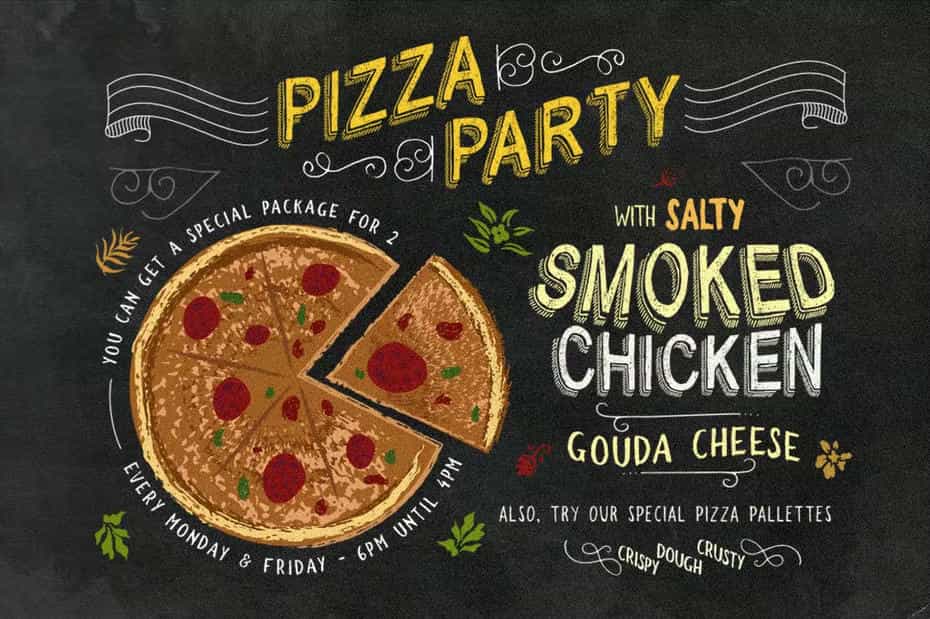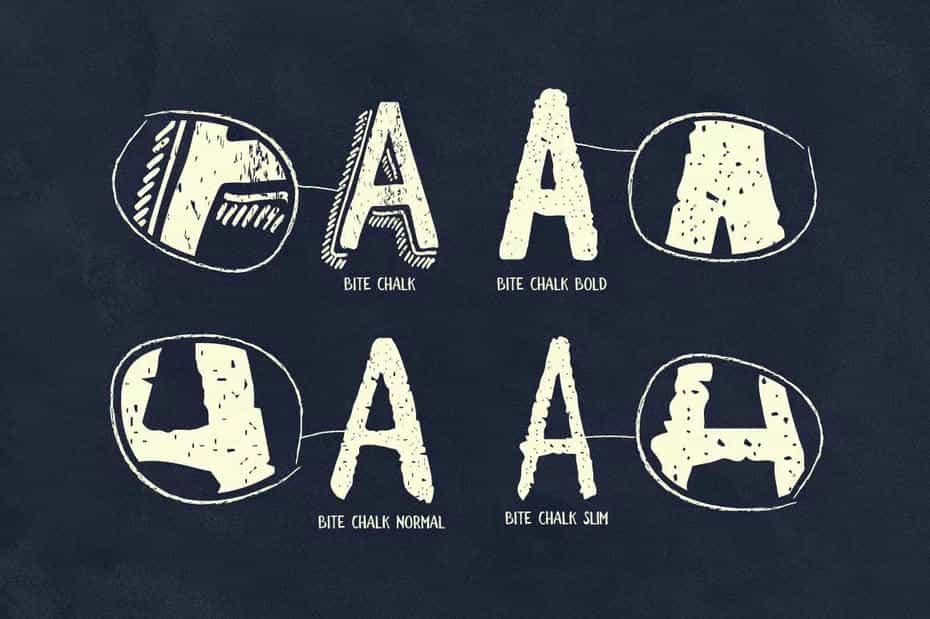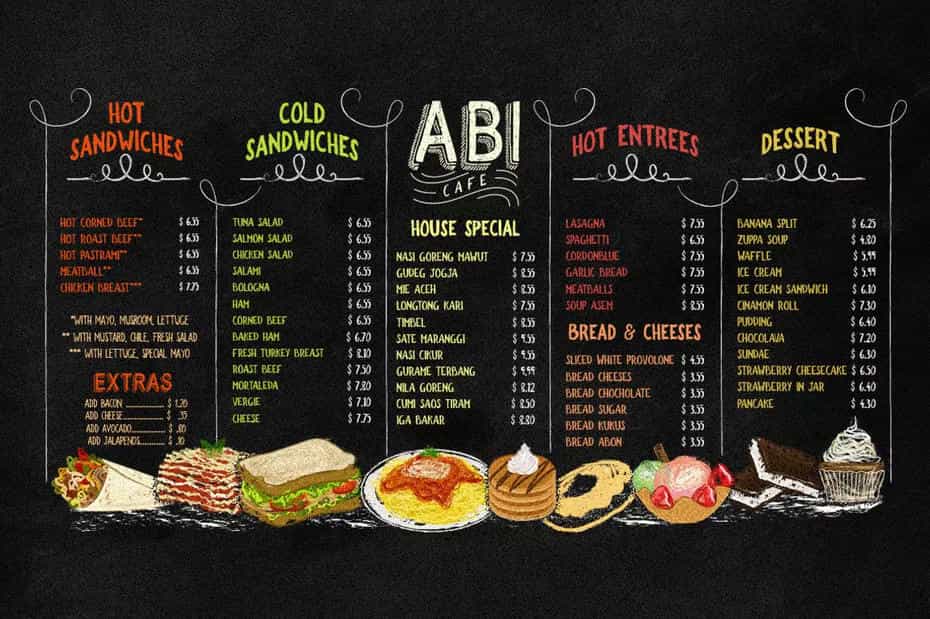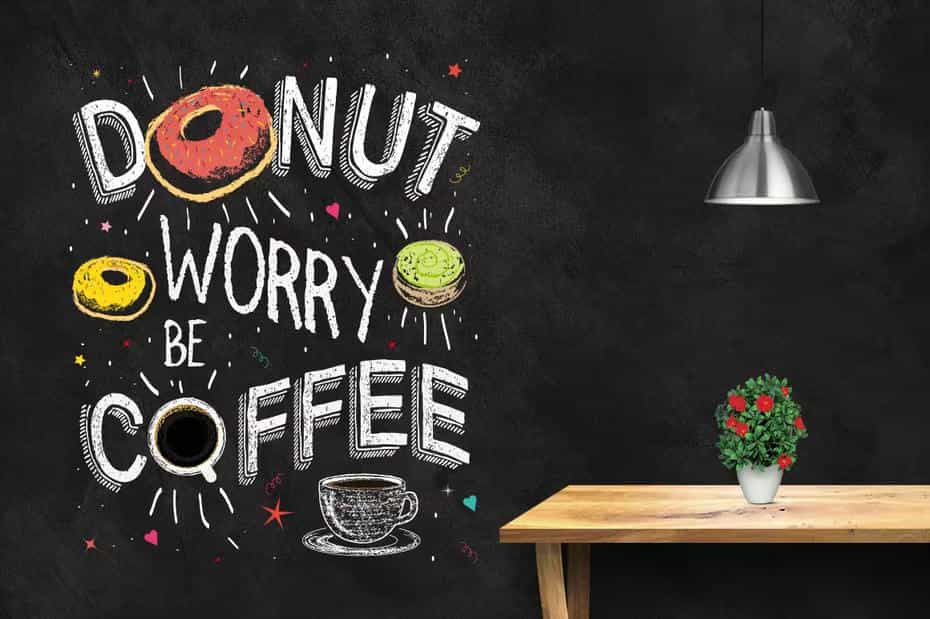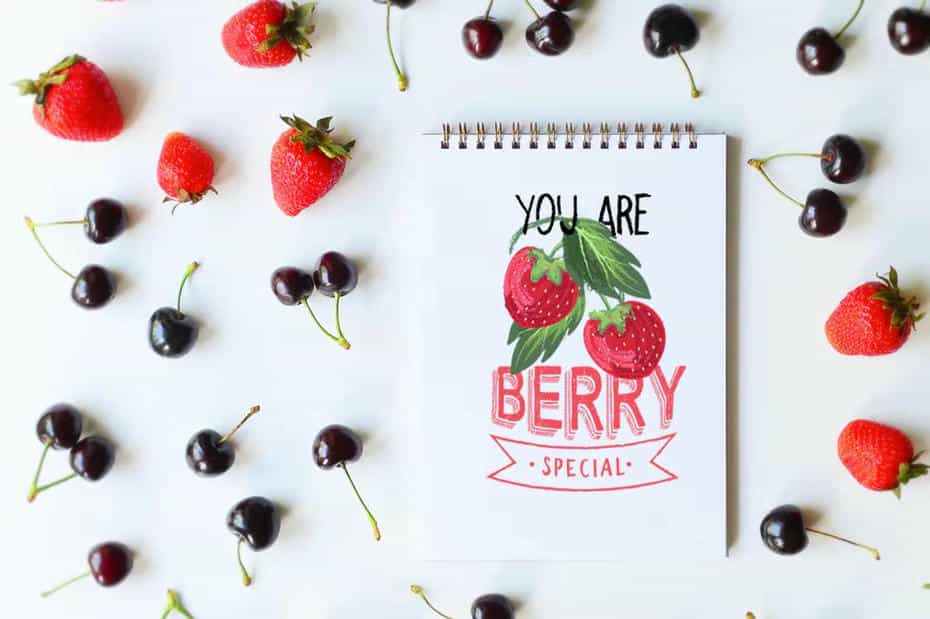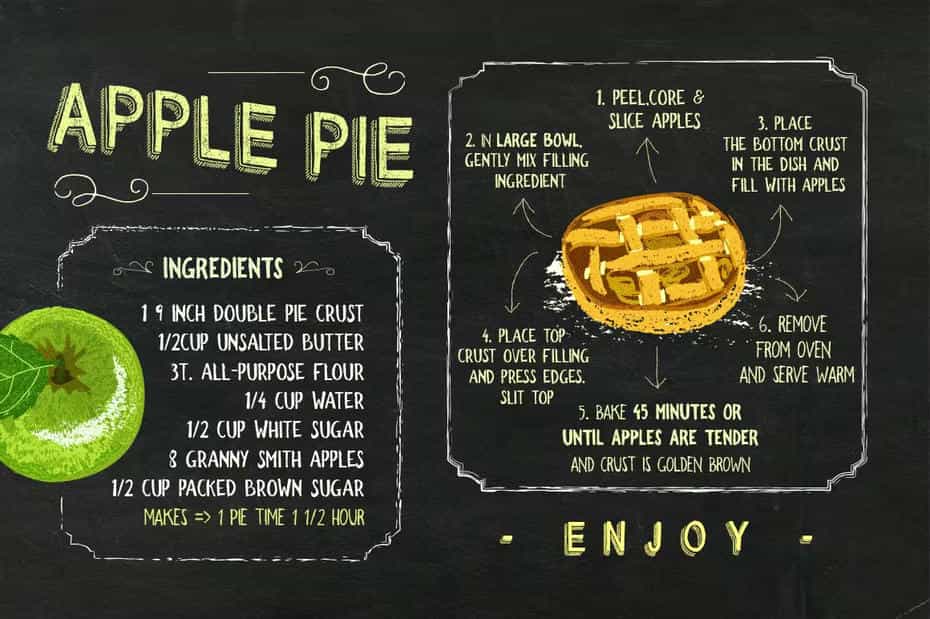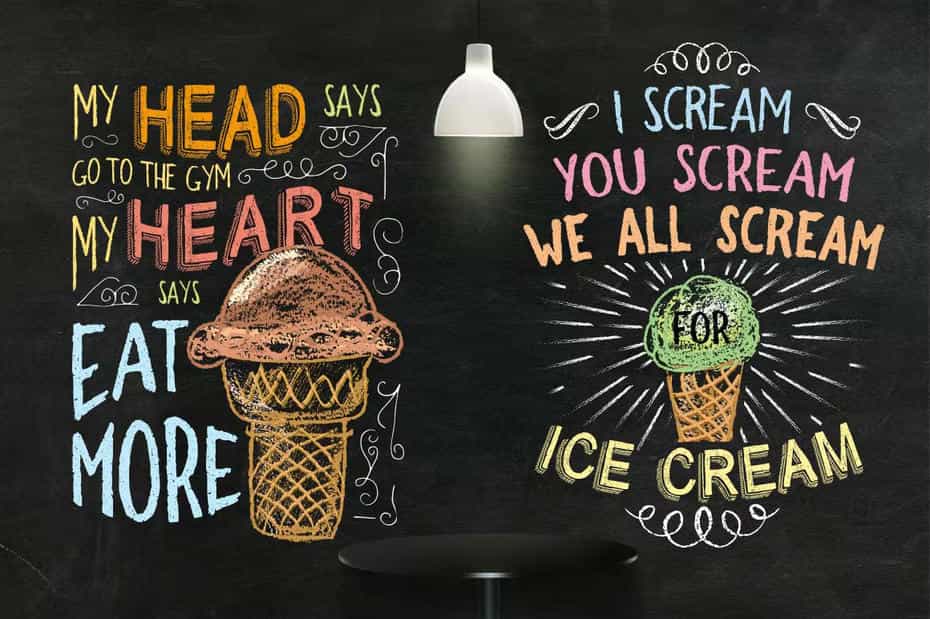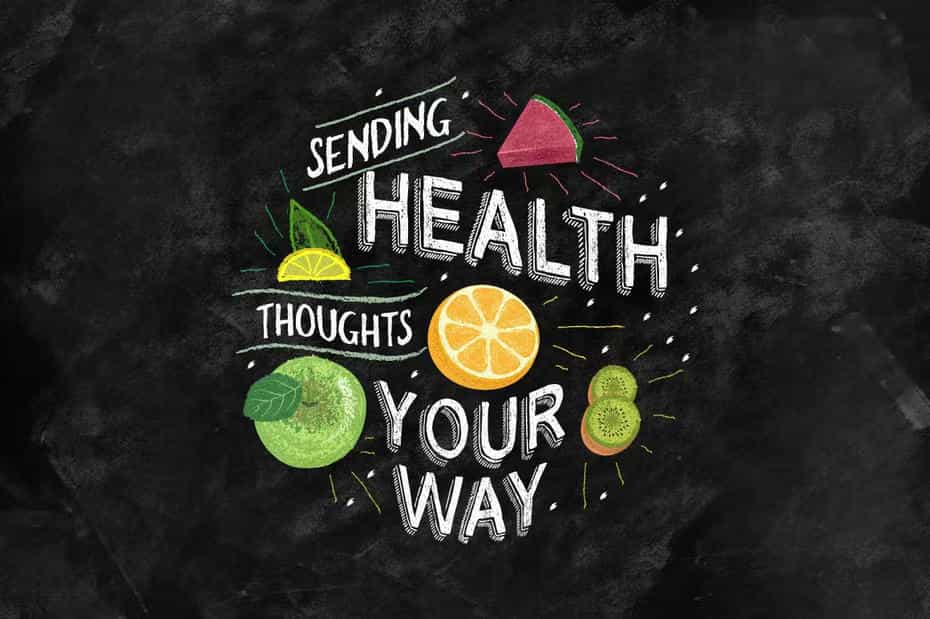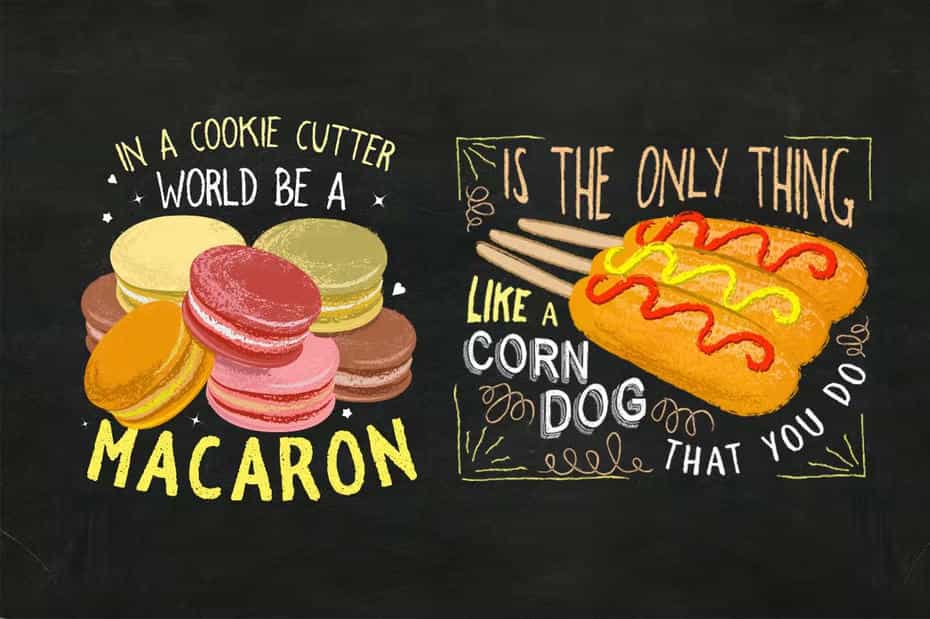
فونت انگلیسی BiteChalk Typeface : این مجموعه شامل یک تایپ فیس می باشد که برای منو کافه و رستوران طراحی شده است. این فونت برای عکس پس زمینه عروسی، تی شرت، پوستر ها و … مناسب می باشد.
• فضا بین حروف: متراکم